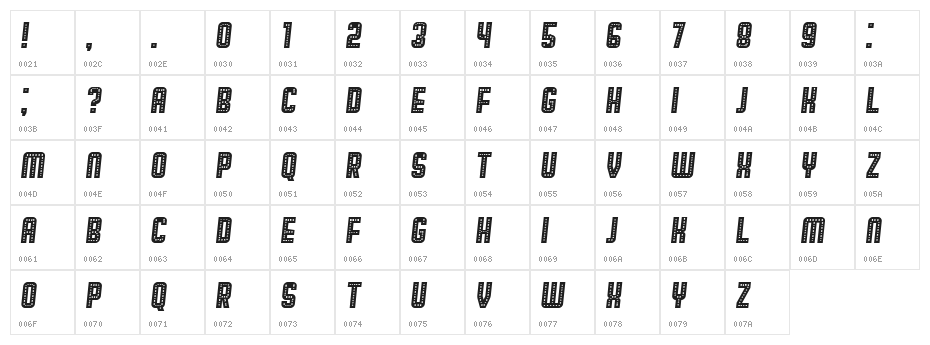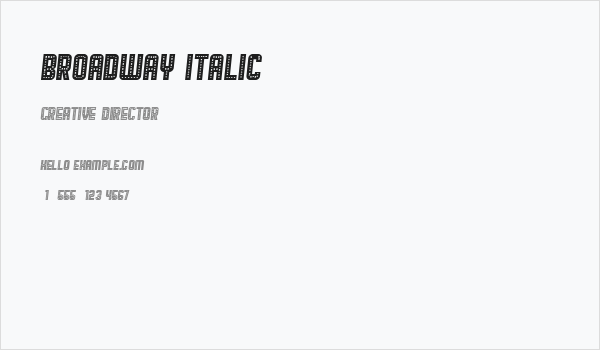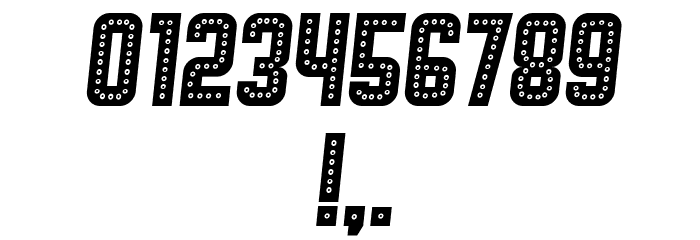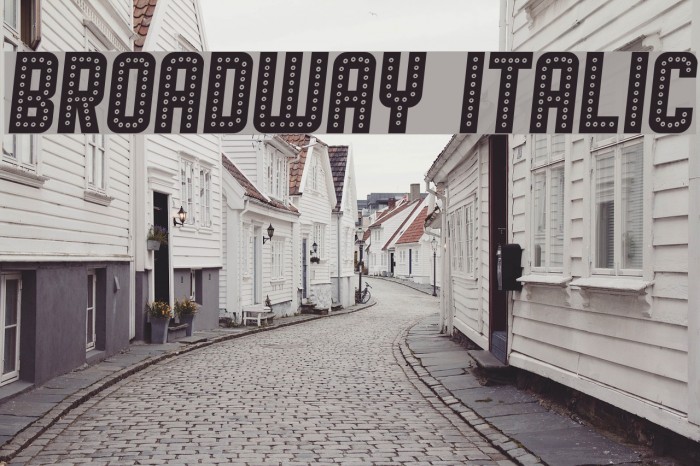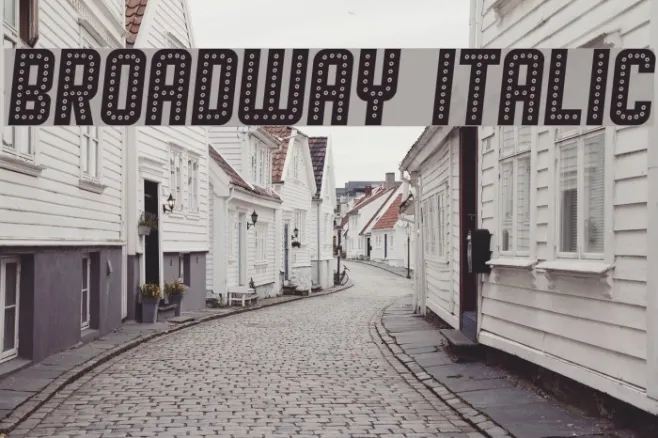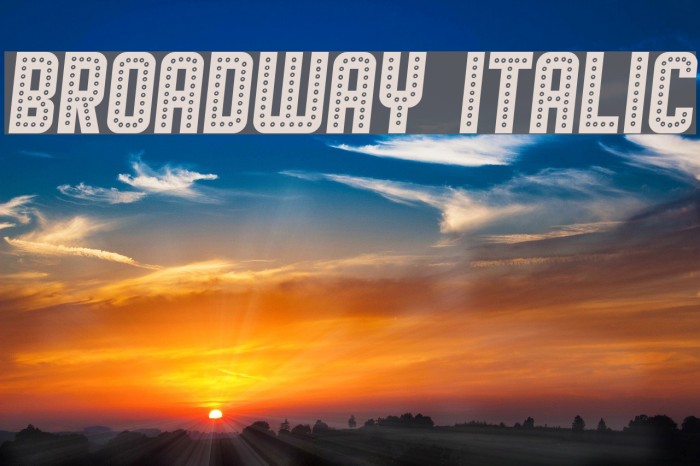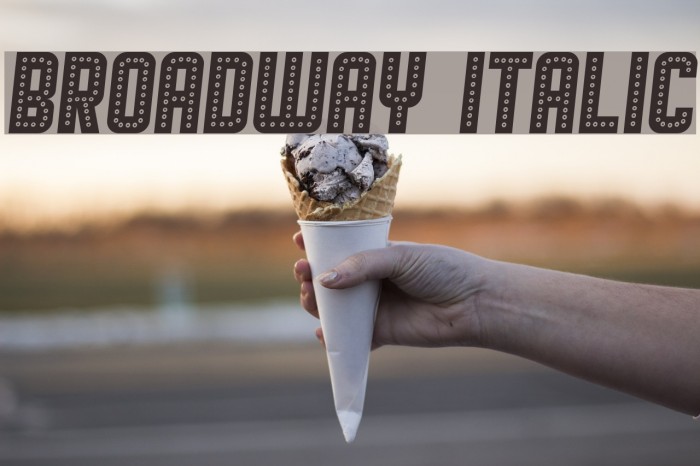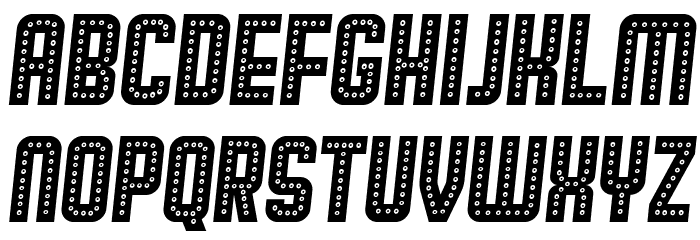
Broadway Italic Font
| Proyectos propuestos | Perfect for use in posters, signage, event invitations, and any project requiring a dramatic and bold typographic presence. |